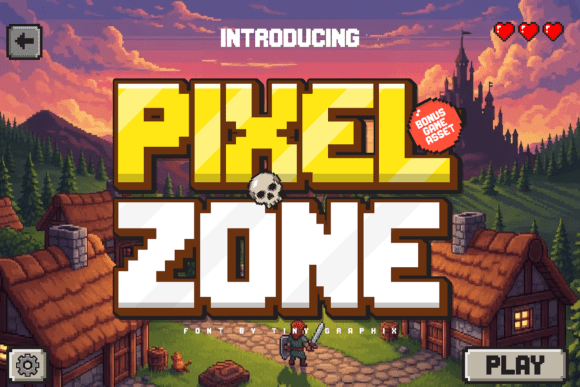
Pixel Zone
การค้นหาองค์ประกอบการออกแบบที่เหมาะสมอาจเป็นเรื่องท้าทาย แต่ Pixel Zone นำเสนอคอลเลกชันที่โดดเด่นซึ่งช่วยยกระดับงานของคุณได้ทันที
ไม่ว่าคุณจะสร้างผลิตภัณฑ์ POD (Print on Demand) คำเชิญงานแต่งงาน หรือกราฟิกโซเชียลมีเดีย Pixel Zone ก็เหมาะสมอย่างยิ่ง